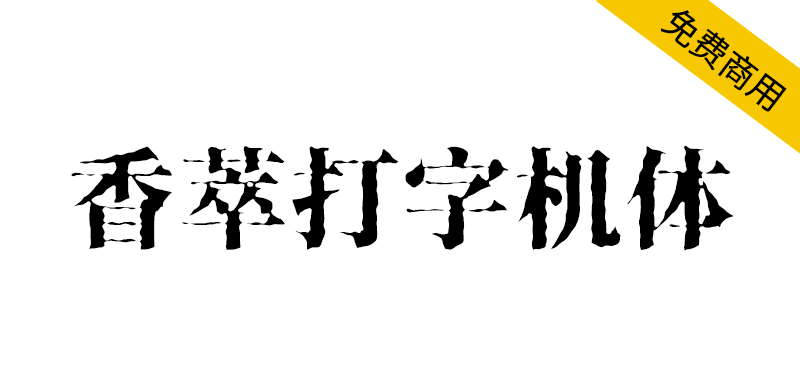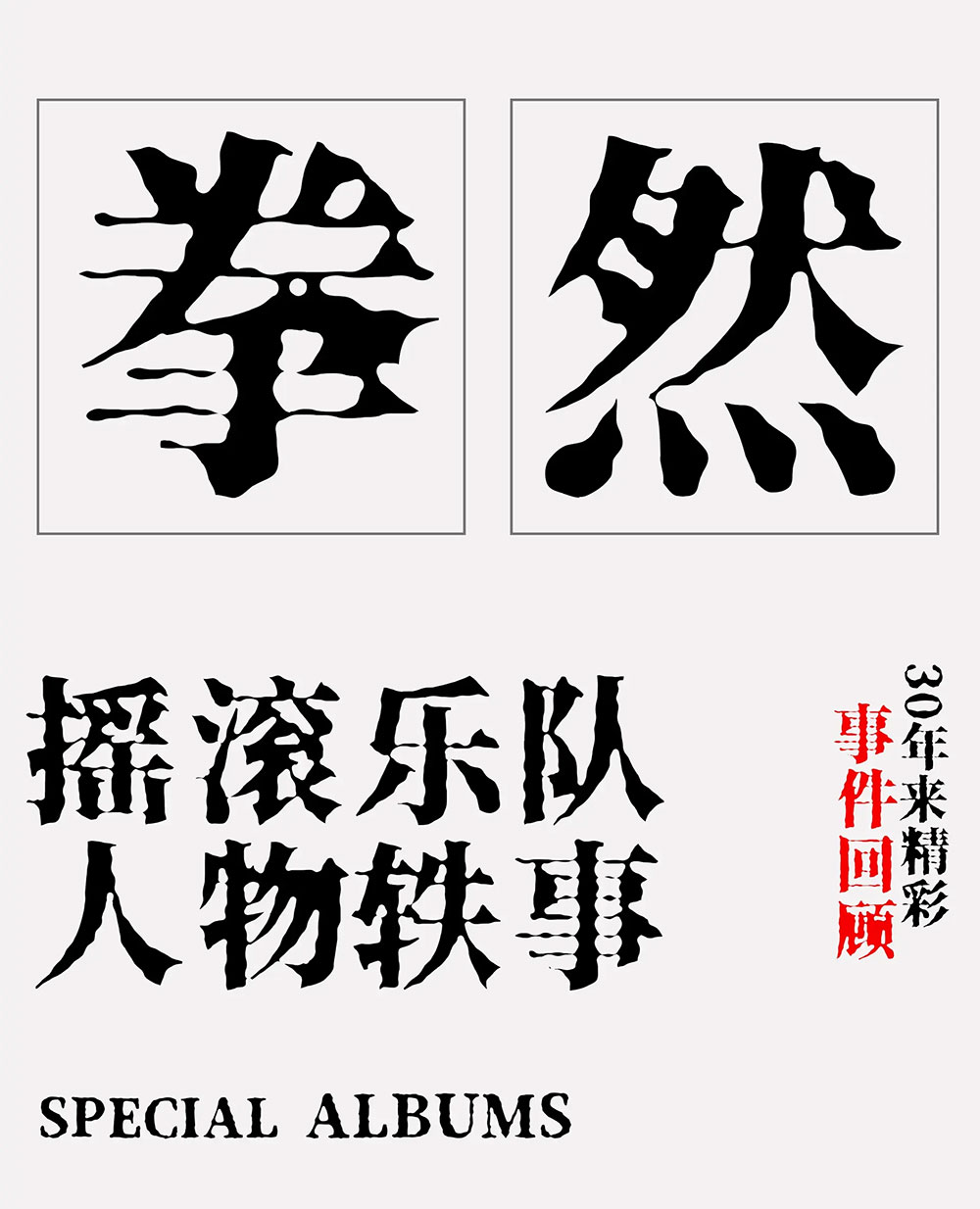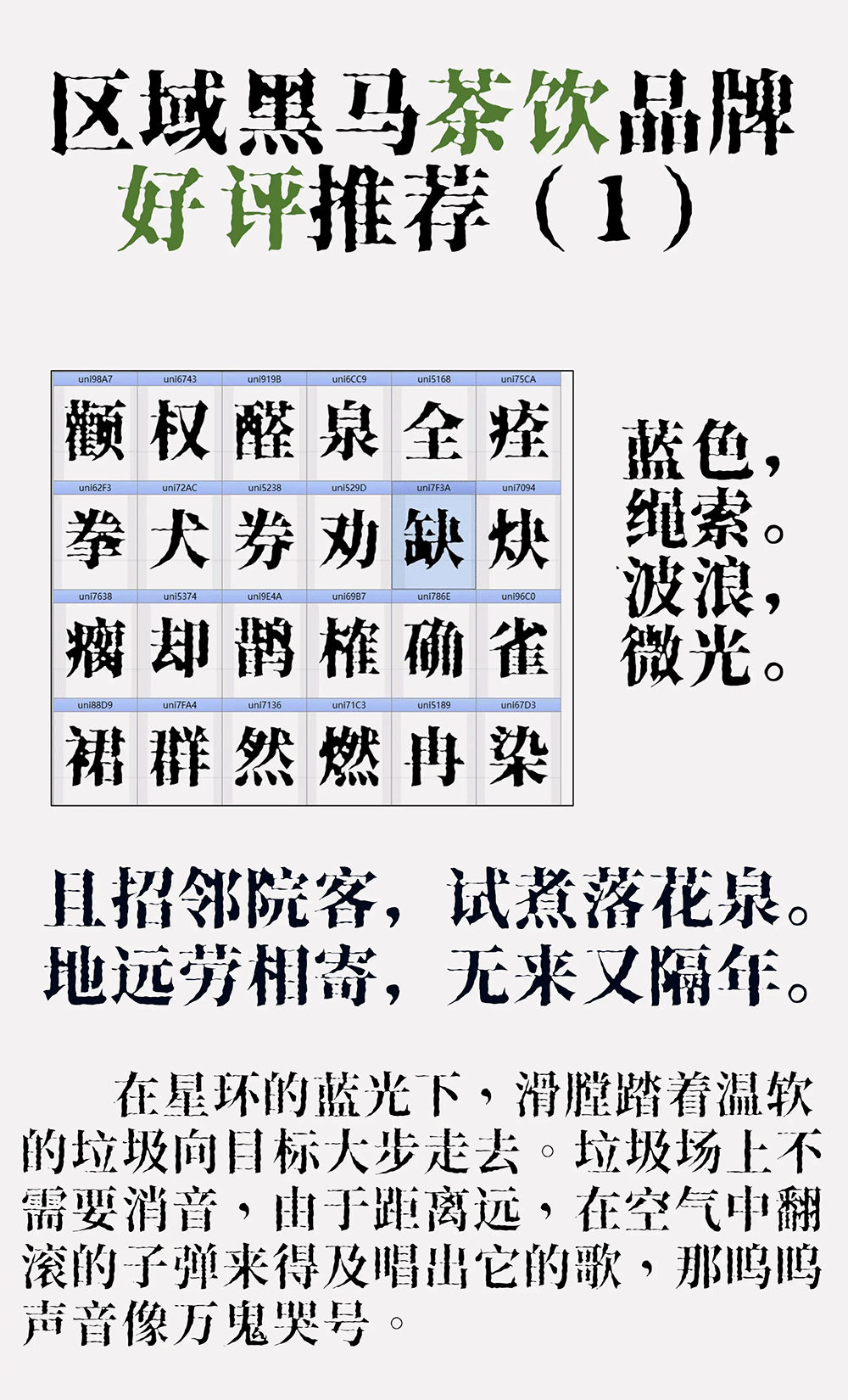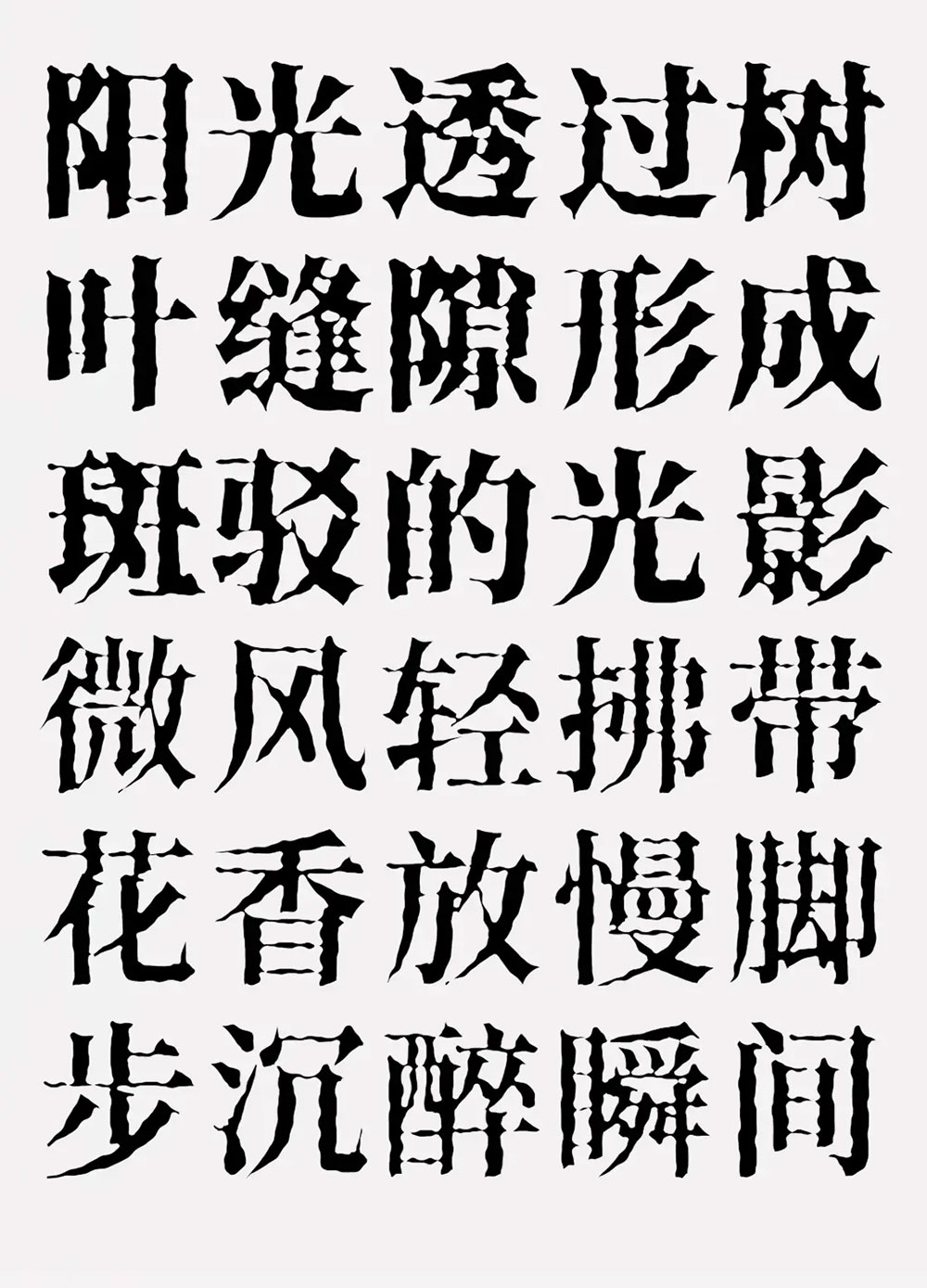
香萃打字机体系列是一款笔画模仿打字机洇墨效果的宋体字家族,包含3个字重。字体的原型是开源项目思源宋体。其中W40与W35的区别在于汉字横画粗细、细节的粘连程度,以及英文字母衬线的不同。制作过程经历人工手动调节,因此目前仅支持GB2312的约7000字符。制作这款字体,是由于先前的香萃刻宋的线条过于尖锐,在偏大字号时显示效果不好。